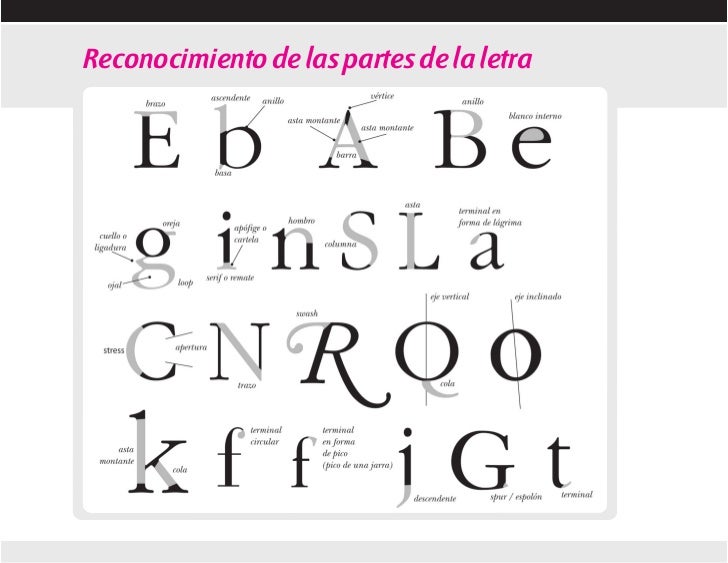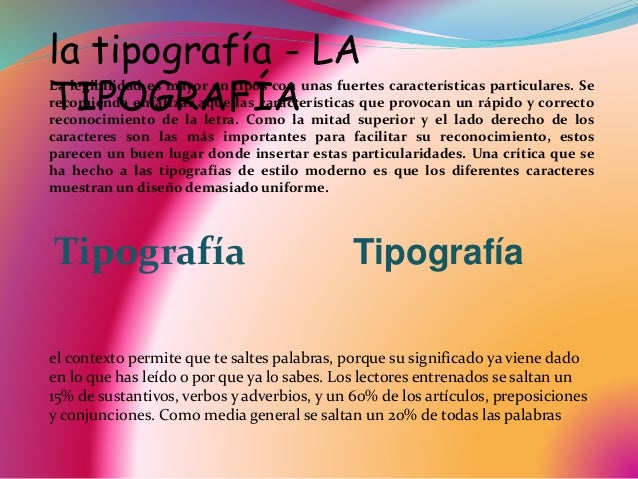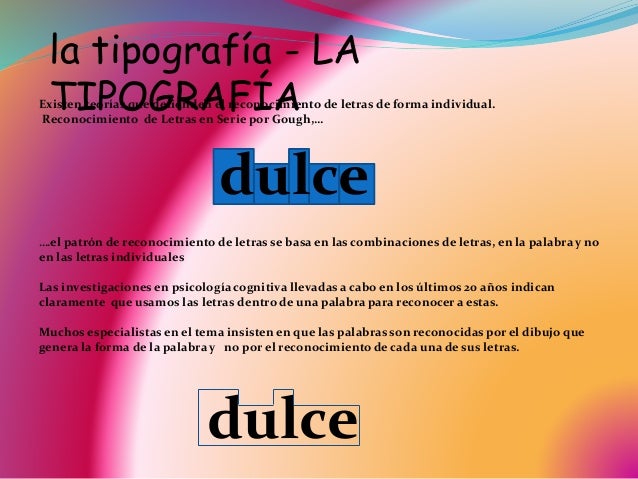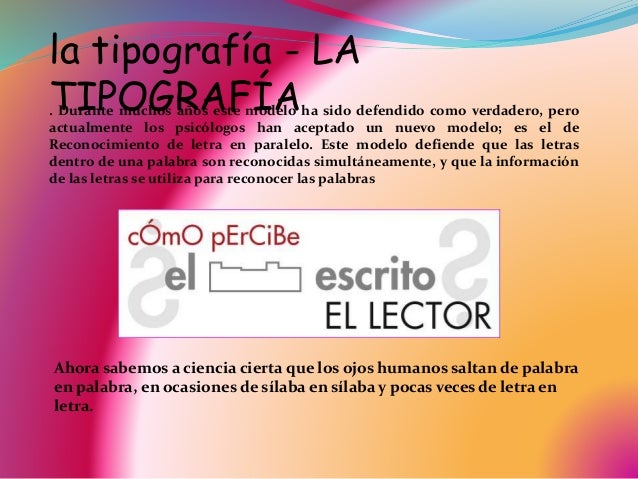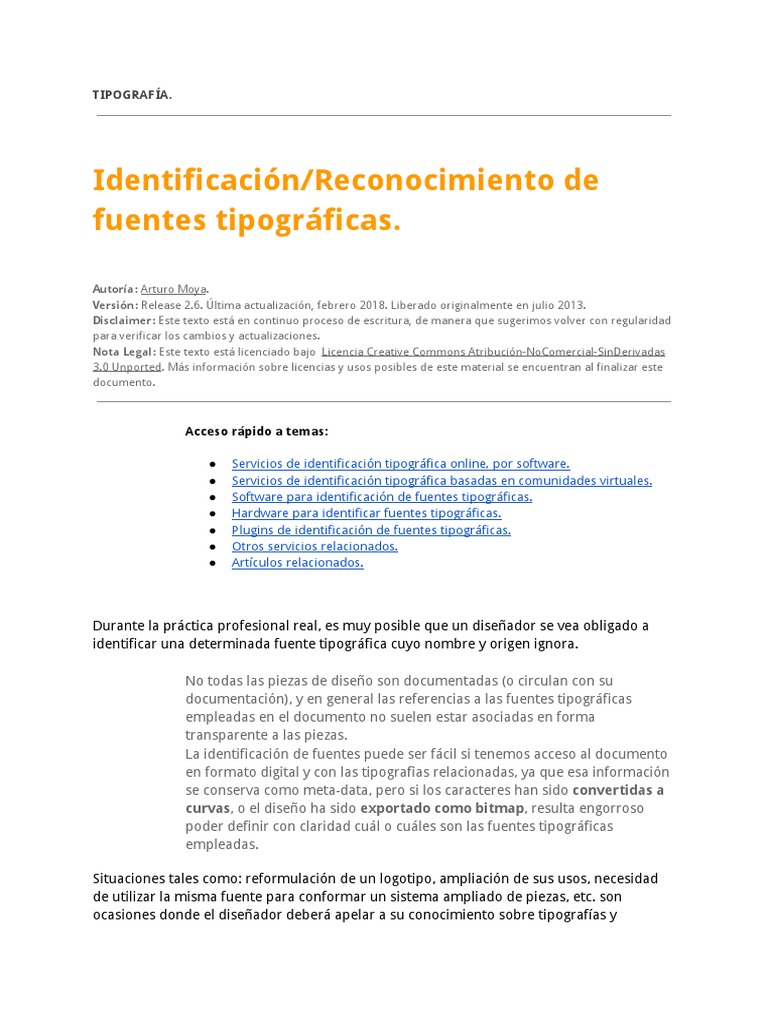
Reconocimiento De Tipografias
Una buena fuente de letra puede ser la diferencia entre que tu texto sea leído o caiga en el olvidoEl contenido es importante, está claro, pero si no está bien presentado o no es legible.
Reconocimiento de tipografias. También ayuda a educar al ojo el saber reconocer la estructura subyacente de varios diseños y las diferencias entre ellos 5 Reconocimiento de las partes de la letra 6 Clasificación de la Tipográfia Para formar estas familias tipográficas debemos nombrar los elementos que nos sirven para clasificarlas e identificarla 1. Las tipografías son uno de los elementos claves para el diseño y la composición de una pieza publicitaria impresa o digital Promueve de forma positiva un mensaje a fin de alcanzar visualización y reconocimiento por parte de las audiencias. Previsualiza online y descarga gratuitamente la fuente tipográfica Diploma Regular TrueType.
Seen a font in use and want to know what it is?. Certificates are a great way to create the spirit of competition, recognize talent and boost motivation Certificates provide written records of precious achievements, hard work and commitment of their owners and therefore, it is imperative for the issuing authority to design and present certificates in a way that it is valued for a lifetime. Cabe destacar que el servicio de Font Of Web es completamente gratuito y ni siquiera amerita procesos de registro Descubrir las tipografías presentes en una web es una tarea sumamente simple que no tomará más de 5 minutos Para comenzar, dirígete a la página de Font Of Web desde el enlace al final de este artículo.
Reconocer una fuente tipográfica vía web Parece mentira, pero con los tiempos modernos en los que vivimos, tuve que conseguir una tipografía a partir de una muestra en un papel No es algo habitual, pero la verdad es que encontré solución Indagué en varias web de reconocimiento de fuentes. Las tipografías OCR (Reconocimiento Óptico de Caracteres) fueron diseñadas para que pudiesen ser leídas tanto por hombres como exploradas y descodificadas por las máquinas gracias a sus formas sencillas esquemáticas OCR A USA Bureau of Standards, 1968 Una de las primeras tipografías creadas para ser reconocidas óptimamente por las. El software de reconocimiento facial en 3D es mucho más avanzado, mediante el uso de cámaras que detectan profundidad, la huella facial puede incluir los contornos y la curva de la cara, así como la profundidad de los ojos y las distancias a partir de puntos de referencia como la punta de tu nariz.
TIPOGRAFÍAS MÁS USADAS Como conocemos en la historia, la etapa del Renacimiento es considerada como la transición de la sociedad entre la Edad Media y hasta llegar a la sociedad moderna, fue un periodo histórico de auge y desarrollo de distintos campos de la sociedad como las ciencias y las artes, donde se retomaron ciertos componentes de las culturas clásicas, griega y romana. De hecho, un tipo de letra particular puede ser la causa principal de que un usuario esté cinco minutos en tu sitio o decida navegar en este por media hora Gran parte del atractivo de una página web recae sobre el tipo de fuente tipográfica que se elija 2 Genera reconocimiento de la marca. Como no estás solo, a alguien se le ocurrió la magnífica idea de crear un identificador de tipografías y como suele suceder, a una buena idea le siguen unas buenas copias No me preguntes cuál fue el primer buscador de tipografía, porque no lo sé Pero lo que sí sé es que hay muchos que puedes usar online y de forma gratuita.
Publicado el de julio de 07 En 1936, el Instituto Alemán de Estándares Industriales estableció el tipo de letra DIN 1451 como la fuente estándar para todas las placas de matrículas del país Esta norma tipográfica pronto se extendió a otros muchos países europeos, y esta fuente y sus variaciones coparon en poco tiempo gran parte de las placas de matrícula del continente. Emplear las mejores tipografías modernas en tus creaciones te permitirá representar de forma crucial una idea en el diseño gráfico, incluso permite ofrecer un aspecto publicitario que garantiza reconocimiento de la marca dondequiera que sea vista Las tipografías modernas le dará vida a la idea que quieres representar, garantiza. Creada en 1991 por Microsoft, se trata de una tipografía de mapa de bits que fue utilizada como tipografía por defecto en el sistema operativo Windows 31, Windows 95, Windows NT 40, Windows 98,.
Más ideas de fuentes Las fuentes usadas en los 80s están obteniendo el reconocimiento que siempre merecieron este 19. Antes de empezar a darte opciones para identificar una tipografía, conviene que sepas exactamente a lo que nos estamos refiriendo por ella Y es que la tipografía no es realmente el tipo de letra que se usa, sino que hablamos de una tarea para elegir y usar diferentes tipos de letras, números y símbolos para poder crear unos trabajos de impresión (o, en este caso, visibilidad online). Conversor de Letras, tipografías & fuentes En este sitio Web existen múltiples estilos de tipos de letras bonitas Con este conversor de fuentes de letras para Instagram y otras aplicaciones se pueden conseguir tipografías lindas con solo copiar y pegar El éxito del convertidor / cambiador de letras.
Las actividades de reconocimiento de letras para preescolares ofrecen la oportunidad de aprender las letras del alfabeto en una manera divertida y atractiva Al proporcionar diferentes formas de practicar las letras, tu hijo estará en mejores condiciones para reconocerlas. De hecho, con menos funciona mejor, al menos en muchas de las ocasiones Reconocer texto mediante la app web La aplicación web también funciona, aunque es algo más peculiar. Tipografías más usadas del mundo del diseño Encuentra fuentes compatibles para windows, linux y mac Tipografías totalmente gratis, la mejor y mayor colección de fuentes tipográficas con gran estética totalmente gratis.
Reconocimiento de caracteres por Juan Martín Seguro que alguna vez habéis visto una tipografía o fuente tipográfica que os ha gustado en algún cartel, un libro, una revista, incluso en la televisión, y habéis querido utilizar para vuestros proyectos, pero que no conocéis como dar con ella. GRUPO DE COMUNICACIÓN KÄTEDRA Blvd Adolfo López Mateos 2 p6 Col San Pedro de los Pinos México, DF , Suscripciones Lada sin costo. Este tipo de fuentes, para las que he desarrollado un sistema matemático de cálculo de proporciones, métricas y kerning que me permite crear tipografías armoniosas de máxima legibilidad, que es mi factor de diseño esencial, y sean cual sean las proporciones iniciales (Condensada, altura de la x, slab serif, Sans serif, etc), también si.
Subes la imagen de la fuente que te interesa averiguar, bien desde tu ordenador o desde una URL Eso sí, la imagen no debe pesar más de 18MB, le das al botón de «continue» Y ¡listo!. Gracias Comentar Me gusta. A todos nos ha pasado alguna vez ver esa tipografía en una imagen y no saber por donde empezar a averiguar de cual se trata Por suerte, hoy me encuentro con otra variante a What The Font, el cual en las últimas oportunidades que lo había utilizado no me había arrojado buenos resultados El sitio en cuestión se llama What Font Is, el cual brinda la posibilidad de subir la imagen con la.
Este tipo de fuentes, para las que he desarrollado un sistema matemático de cálculo de proporciones, métricas y kerning que me permite crear tipografías armoniosas de máxima legibilidad, que es mi factor de diseño esencial, y sean cual sean las proporciones iniciales (Condensada, altura de la x, slab serif, Sans serif, etc), también si. Publicado el de julio de 07 En 1936, el Instituto Alemán de Estándares Industriales estableció el tipo de letra DIN 1451 como la fuente estándar para todas las placas de matrículas del país Esta norma tipográfica pronto se extendió a otros muchos países europeos, y esta fuente y sus variaciones coparon en poco tiempo gran parte de las placas de matrícula del continente. Tania produce material pedagógico multimedia, el cual vende en su página web himokicom, además de ser ilustradora infantil De ahí su gusto por esta tipografía estilo hand drawn “Sansa Kid para proyectos infantiles, por ejemplo libros de cuentos con párrafos cortos o proyectos con estilo “handdrawn”, ya que cualquiera se puede sentir identificado con ella, ya que nos recuerda a.